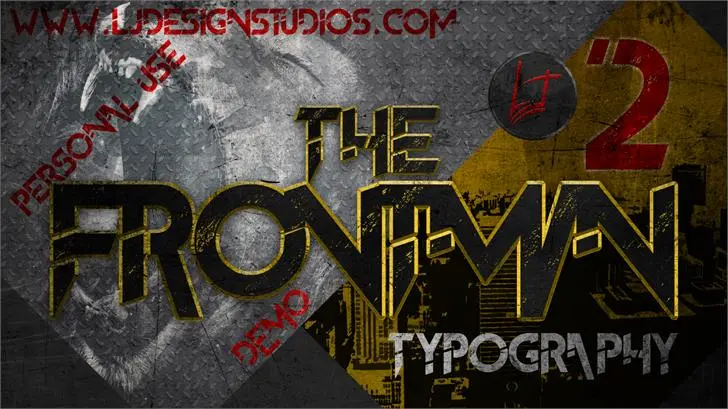
The FrontMan2 Font – Download Grátis
A fonte The FrontMan2 é uma escolha ideal para quem busca estilo sem perder a elegância na tipografia. Criada pelo designer lj.design, essa fonte se destaca no segmento de graffiti com linhas modernas e vibrantes que combinam perfeitamente com qualquer projeto grafico urbano ou artístico criativo. O The FrontMan2 oferece uma gama completa de letras maiúsculas, minúsculas, números e símbolos, o que lhe permite personalizar seu design de maneira impecável. Além disso, sua simplicidade e modernidade fazem deste um recurso versátil para designers e criadores de conteúdo em diversos campos, desde a criação do logotipo até a produção de texturas digitais. Para obter as letras comerciais, simplesmente siga o link ou entre em contato com o designer. Este é apenas mais um elemento que contribui para a incrível qualidade da The FrontMan2 e sua função como uma fonte indispensável para qualquer projeto visual impecável.